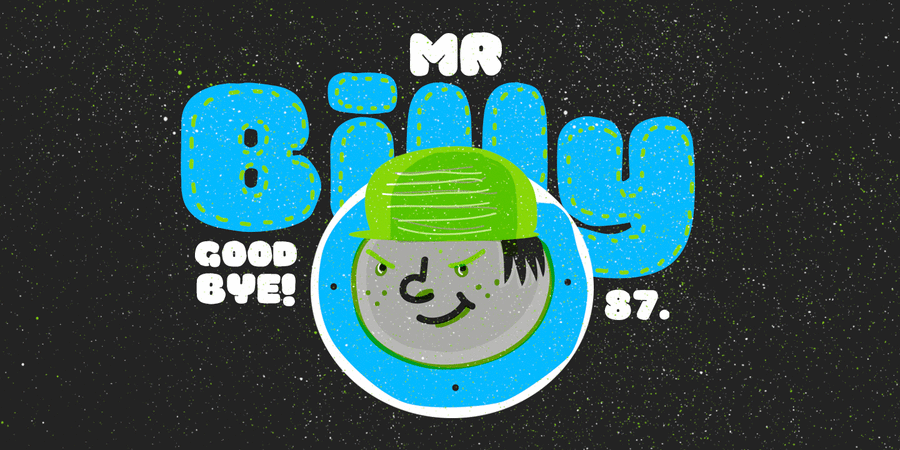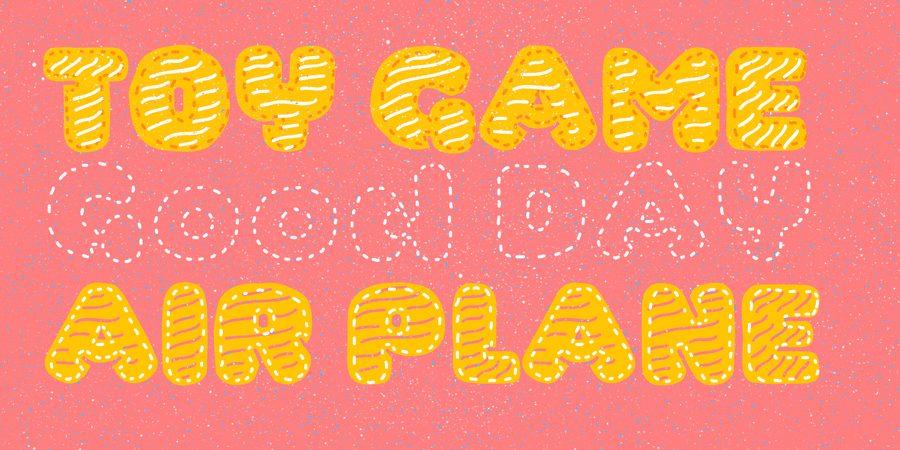
Опис гарнітури La Mona KidsШрифт Mona Kids – самый игривый, улыбчивый и наивный шрифт в мире. Его легко перепутать с пончиком и сьесть. В этой корзине пирожных более 550 глифов! Шрифт разработан в 2016 году Родриго Арая Салас.
Асоціації з сімейством шрифтів La Mona KidsОсобистість і характер гарнітури:
веселий, пузатий, задерикуватий, смішний, доброзичливий, добродушний, добрий, радісний, грайливий, привітний, пустотливий, оригінальний, свіжий, стиглий, соковитий, смачний, важкий, помітний, яскравий, дитячий, наївний, карикатурний, милий, мультяшний, дотепний, домашній, літній, М'який, щедрий, пишний, затишний, приємний, живий, гладенький, святковий, тісний, товстий, прикольний, няшний, усміхнений, апетитний, солодкий, щасливий, зимовий, сніжний, творчий, фруктовий, ягідний, рясний, насичений, пухкий, спекотний, симпатичний, вернакулярний, прозорий, ніжний
молоко, булочка, десерт, солодощі, кондитерська, випічка, булочна, м'яка іграшка, дитяча книжка, фарби, фарба, гумор, анімація, іграшка, дитяче харчування, їжа, закуска, зоопарк, клоун, розфарбування, гра, фаст фуд, пончик, зоомагазин, тварини, відпочинок, цирк, мультфільм, дитсадок, дитячий ранок, сік, канікули, торт, цукерки, крем, згущене молоко, варення, подарунки, свято, день народження, шоу, телебачення, соус, сметана, кетчуп, жуйка, підгузок, чіпси, котики, фрукти, мармелад, розваги, зима, сир, графіка, ілюстрація, дім, ранок, спальня, подушка, родина, малюк, собачка, акварель, Christmas, смузі, море, АСМР, Хюґе Гарнітура асоціюється з віком: